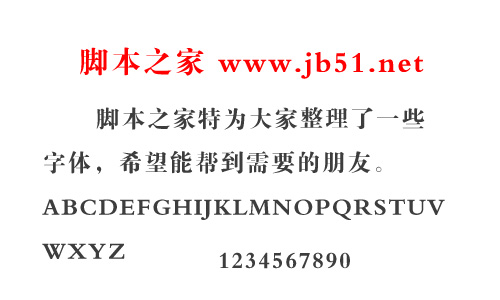
方正大標(biāo)宋_GBK字體是方正字體庫(kù)中的一種字體,方正大標(biāo)宋源自1970年上海字模一廠(chǎng)設(shè)計(jì)的行頭宋,是專(zhuān)門(mén)為大字號(hào)標(biāo)題設(shè)計(jì)的,可以說(shuō)是方正小標(biāo)宋的姊妹。相對(duì)于方正小標(biāo)宋,方正大標(biāo)宋的筆畫(huà)略粗,中宮略為收緊,這符合大字宜緊密,小字宜寬綽的書(shū)法規(guī)律。但總體而言,這兩款字體風(fēng)格很接近。方正大標(biāo)宋筆畫(huà)圓潤(rùn)飽滿(mǎn),字形凝重沉穩(wěn),適用于報(bào)刊、書(shū)籍的各類(lèi)標(biāo)題字。喜歡的朋友們可以前來(lái)下載使用。